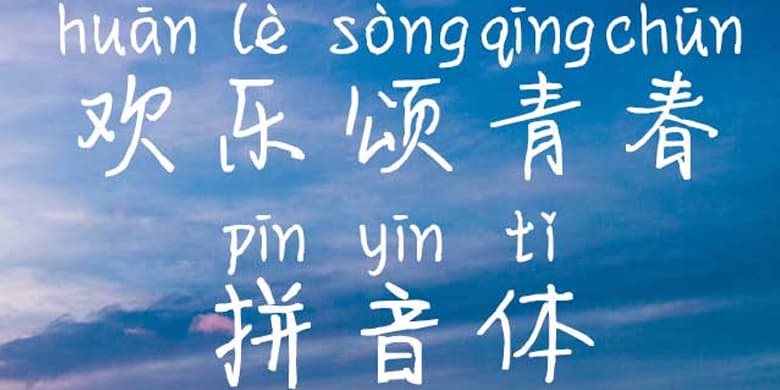
品牌:方正手迹设计师:王航发行时间:2020字库编码:大陆简体(GB2312-80)分类:常规书写·硬笔字体属性:精品字
欢乐颂青春拼音体是一款创意手写字体。线条挺拔苍劲,字形端庄秀美,青春活泼又从容优雅。不仅适用于现代诗歌、短文的排版,还可用于社交网络的个性化用字,文艺类的书刊、品牌广告和产品包装设计。